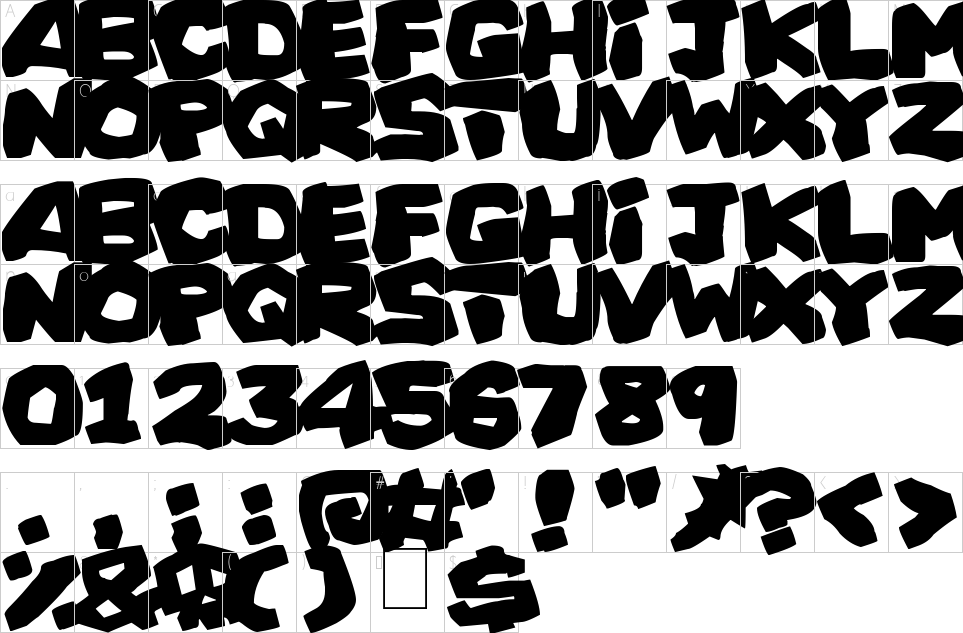
Prehistoric Caveman Font é uma fonte de desenho de cavalaria pré-histórico, ideal para estilos de arte vintage e retro. Desenvolvida por Darrell Flood, esta fonte é perfeita para personalizar suas criações digitais com um toque de simplicidade e estilo. Com suas formas geométricas e desenhos minimalistas, a fonte captura a essência do estilo de arte de um cavalo pré-histórico, criando um ambiente único e envolvente para qualquer projeto. Descarregada milhares de vezes, a Prehistoric Caveman Font oferece uma maneira divertida e criativa de incorporar elementos do passado no seu trabalho. Combinada com outras fontes, ela pode reviver um mundo distante, onde as formas geométricas eram o design de moda.